Creación Efectiva de Tipografía Digital en Procreate
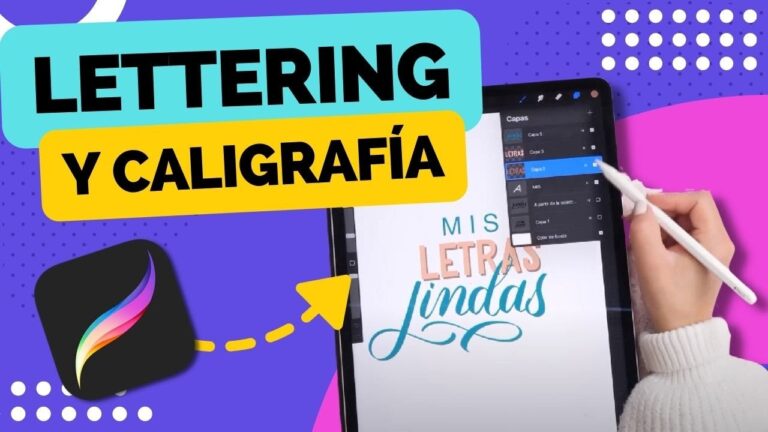
La creación de tipografía digital con Procreate ha revolucionado el mundo del diseño gráfico, concediendo a artistas y creativos dar rienda suelta a su imaginación de manera intuitiva y accesible. Esta herramienta, conocida por su versatilidad y facilidad de uso, ofrece una plataforma ideal para desarrollar fuentes personalizadas que reflejan la identidad única de cada diseñador. En este artículo, indagaremos los pasos esenciales para dominar la tipografía digital en Procreate, así como consejos y trucos que facilitarán el proceso creativo. ¡Sumérgete en el fascinante universo de la tipografía digital y descubre cómo transformar tus ideas en letras impactantes!
¿Cómo se crea una tipografía digital?
Crear una tipografía digital es un proceso emocionante y accesible, especialmente con las herramientas adecuadas. Una de las mejores opciones disponibles es MyScriptFont, conocida por su facilidad de uso. Este programa permite a los usuarios personalizar su fuente sin complicaciones técnicas, lo que lo convierte en una excelente opción tanto para principiantes como para diseñadores experimentados.
Para comenzar, solo necesitas descargar una plantilla en la que escribirás tu fuente. Esta plantilla está disponible en formatos PDF o PNG, lo que facilita su impresión y uso. Una vez que hayas completado la plantilla con tus letras y caracteres deseados, simplemente la subes a la aplicación y ella se encargará del resto, generando tu tipografía digital en pocos minutos.
El resultado es una fuente única que refleja tu estilo personal y creatividad. Con MyScriptFont, puedes experimentar con diferentes formas y estilos, lo que te permitirá crear una tipografía que se adapte perfectamente a tus proyectos. No hay límites en la personalización, así que ¡deja volar tu imaginación y comienza a diseñar tu propia tipografía digital hoy mismo!
¿Qué tipos de formatos existen para la tipografía digital?
La tipografía digital requiere formatos específicos para su almacenamiento y uso adecuado. Entre los más destacados se encuentran el formato TT (TrueType), que ofrece escalabilidad y compatibilidad en diversas plataformas; el PS1 (PostScript de tipo 1), conocido por su calidad en la impresión; y el Open Type Font, que combina las ventajas de los anteriores y permite una mayor flexibilidad en el diseño. Estos formatos son esenciales para garantizar que las fuentes se visualicen y se impriman correctamente en diferentes dispositivos y aplicaciones.
¿Es posible utilizar Procreate para diseñar tipografías?
Procreate es una herramienta versátil que va más allá de la simple ilustración digital, concediendo a los usuarios crear fuentes personalizadas de manera intuitiva. Con su amplia gama de pinceles y herramientas de diseño, puedes experimentar con diferentes estilos tipográficos, desde caligrafía elegante hasta tipografías más modernas. La interfaz amigable de Procreate facilita el proceso de creación, haciendo que incluso los principiantes puedan dar rienda suelta a su creatividad.
Una vez que hayas diseñado tus letras en Procreate, puedes exportarlas en formatos compatibles para convertirlas en fuentes utilizables. Esto abre un mundo de posibilidades para diseñadores y artistas que buscan añadir un toque personal a sus proyectos. Al combinar la potencia de Procreate con software especializado para la creación de tipografías, puedes llevar tus diseños al siguiente nivel y compartir tus creaciones únicas con el mundo.
Domina el Arte de la Tipografía en Procreate
La tipografía es un elemento fundamental en el diseño gráfico, y dominarla en Procreate puede transformar tu trabajo creativo. Esta aplicación ofrece herramientas intuitivas que permiten experimentar con diferentes estilos de letra, tamaños y colores, brindando la libertad de personalizar cada aspecto de tu tipografía. Con un poco de práctica, puedes crear composiciones visuales que no solo sean estéticamente agradables, sino que también transmitan el mensaje adecuado de manera útil.
Además, Procreate facilita el uso de pinceles y texturas que pueden dar vida a tus letras, haciéndolas más dinámicas y únicas. Al combinar tipografía con ilustraciones, puedes lograr un impacto visual sorprendente y cautivador. Aprender a jugar con la jerarquía y el espaciado en tus diseños te permitirá destacar información clave y guiar la mirada del espectador. Así, dominar el arte de la tipografía en Procreate no solo enriquecerá tu habilidad como diseñador, sino que también potenciará la comunicación visual de tus proyectos.
Técnicas Esenciales para Diseños Tipográficos
La tipografía es un arte que va más allá de la simple elección de fuentes. Para lograr diseños tipográficos impactantes, es fundamental comprender la jerarquía visual. Utilizar diferentes tamaños, pesos y estilos de letra permite guiar la atención del espectador hacia los elementos más importantes del mensaje. Una buena jerarquía no solo mejora la legibilidad, sino que también aporta dinamismo y equilibrio al diseño.
La creación de tipografía digital con Procreate se presenta como una herramienta poderosa y accesible para diseñadores y artistas. Su interfaz intuitiva y la variedad de pinceles disponibles permiten una personalización sin límites, transformando ideas en tipografías únicas y creativas. Al explorar esta técnica, no solo se amplía el repertorio artístico, sino que también se fomenta la innovación en el diseño gráfico, abriendo nuevas puertas a la expresión personal y profesional en el mundo digital.